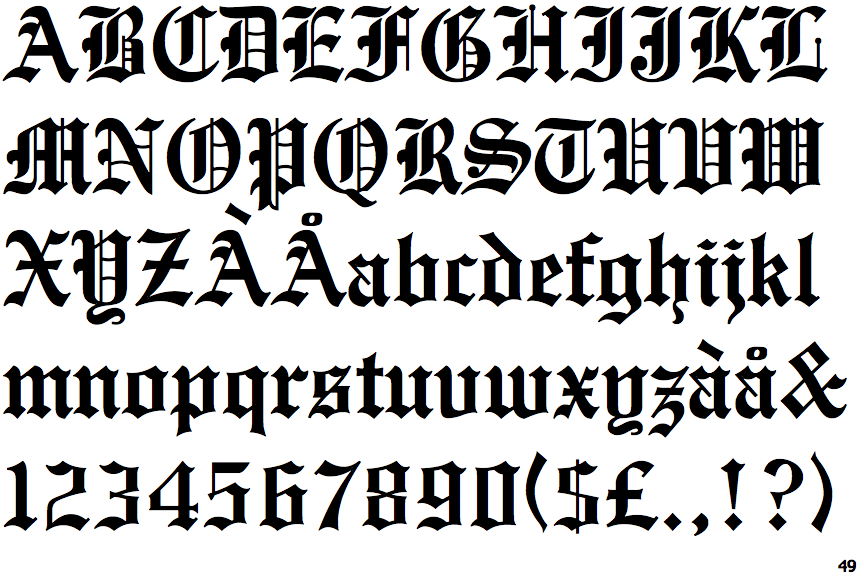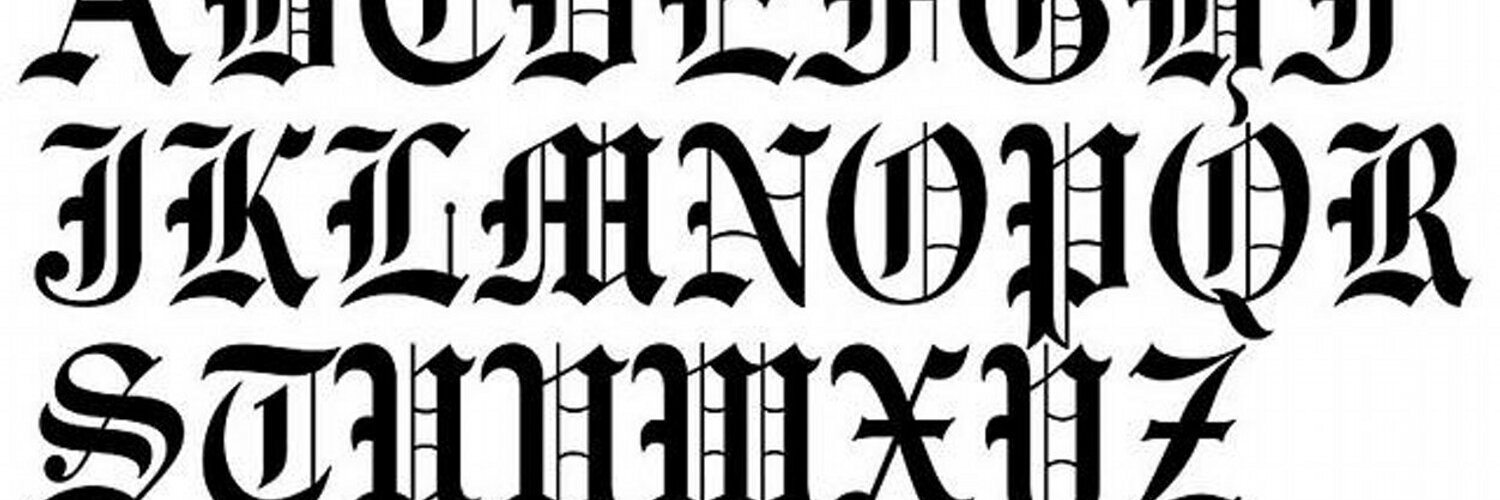
Готические кириллические шрифты для Photoshop и не только
Готика была популярным стилем шрифта в средние века с 1200 по 1500 год.
Термин произошел от итальянцев, которые использовали его для обозначения «варварских» букв Blackletter. Кроме того, такие шрифты отражают популярность этого стиля в то время, когда гравировка на медной пластине была популярной техникой для воспроизведения иллюстрированного материала; примерно с 1530 по 19 век. Хотя настоящие строчные буквы никогда не разрабатывались многие готические варианты идеально подходят для текста, состоящего только из заглавных букв, обычно набранного мелким шрифтом. Например, они очень популярны при использовании на визитных карточках. Крошечные засечки придают им особый вид. Дизайн отражает как надежность шрифтов без засечек, так и элегантность шрифтов с засечками.
Мы подобрали для вас несколько вариантов готических шрифтов с декоративными элементами, характерным дизайном, узнаваемом по художественным произведениям.
Baldur
Bleeding Cowboys
DS Kork
GothicI
GranvilleC
King EdwardC
Victorian Gothic One
Viking